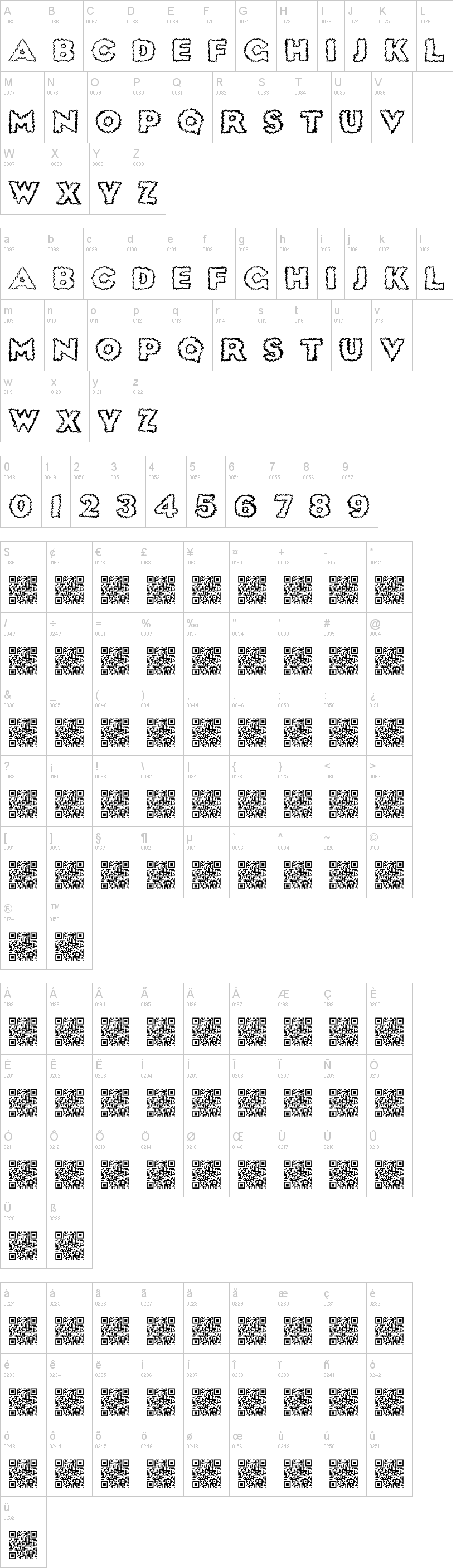
Sick Dream 字体是一种特殊的手写风格字体,具有浓烈的个性和艺术感。它主要使用细线和粗线相结合的方式呈现出一种“斑驳不均”的效果,同时还有一些类似刷子的笔画,使得整个字体看起来非常有趣和独特。 Sick Dream 字体适用于设计师和创意人士,可以用来设计各种海报、广告、包装等等,能够很好地表达出品牌的个性和独特性。内容介绍
Sick Dream是一款非常不错的手写艺术字体,具有很好的视觉感,适合于文化类的宣传设计、商业类品牌的广告和产品包装设计以及个性化文字排版等较多场景。